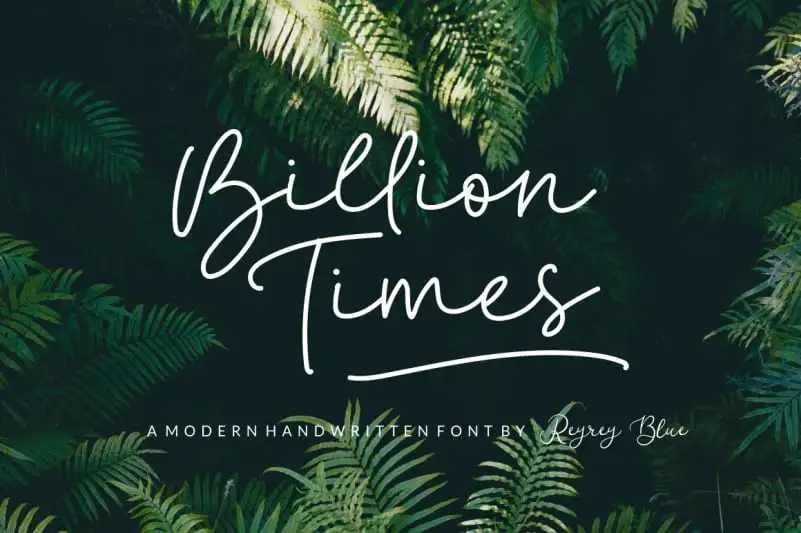
Billion Times Handwritten Font – Download Grátis
Introduzimos a Billion Times Handwritten Font, uma nova tipografia script manuscrita que oferece um visual moderno e fresco. Inspirada na escrita natural das pessoas, esta fonte foi projetada para ser comoventemente autêntica, permitindo-a se destacar em diversas aplicações gráficas. Perfeita tanto para logos quanto para anúncios, letras de citação e cartas de convidado, a Billion Times Handwritten Font é perfeitamente adaptável para blogs, cards comerciais, apresentações e muito mais. Sua versatilidade torna-a uma escolha ótima para estilos que valorizam o realismo da escrita, sem perder seu caráter moderno. ReyreyBlue, nosso criador de fontes, comprou cuidadosamente em sua característica a intenção natural e orgânica do texto manuscrito. É a fonte perfeita para quem quer dar ao seu trabalho um toque único e autêntico.